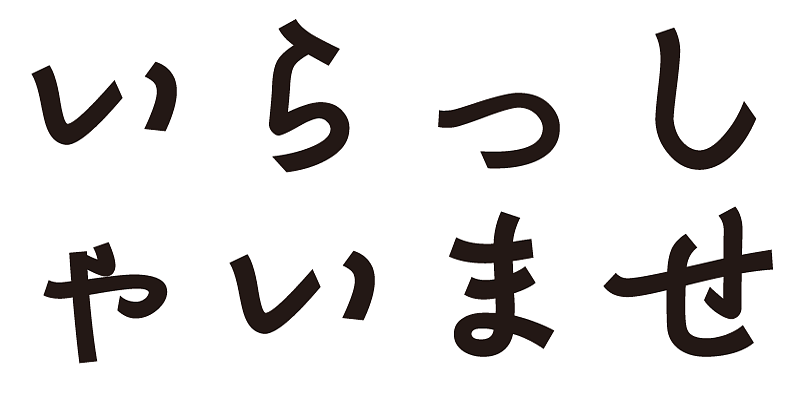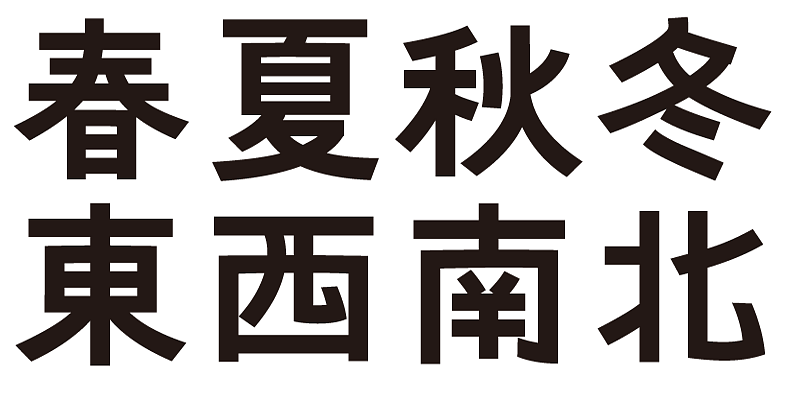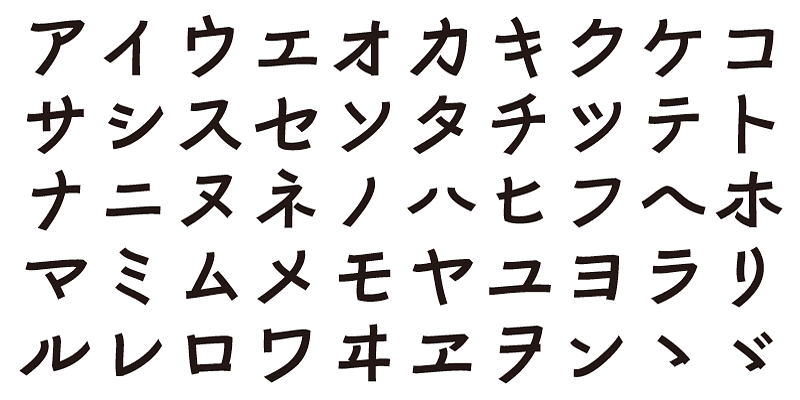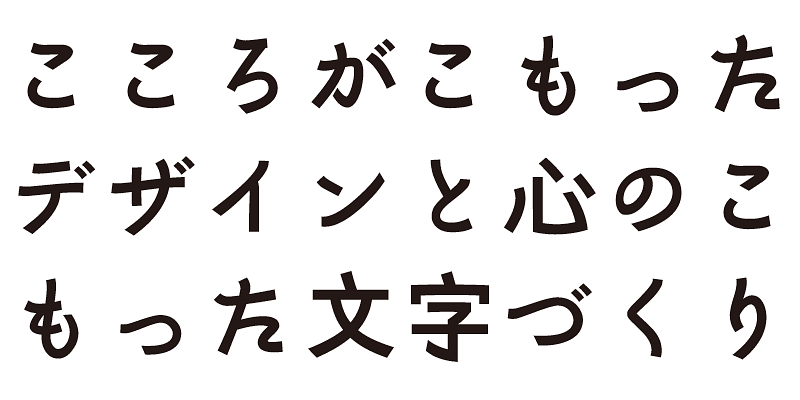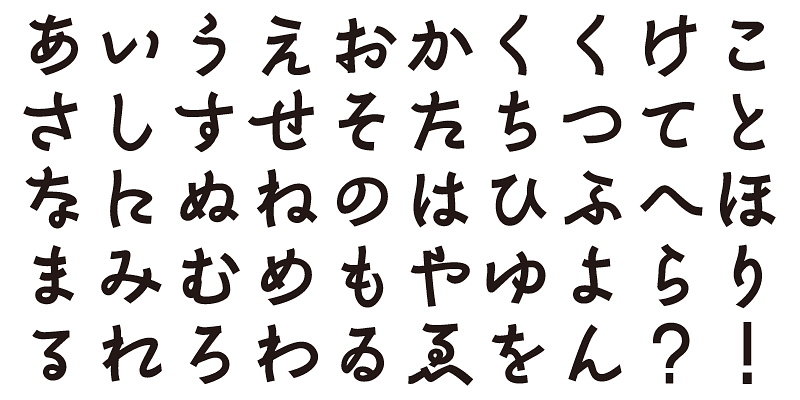
Diese Schrift im Gotikstil mit kräftigen Pinselstrichen basiert auf dem kalligrafischen Stil der chinesischen Sechs-Dynastien-Zeit (220–589 n. Chr.) sowie auf der traditionellen „Li Shu“-Kalligrafie (隶书; auch Clerical Script genannt).
Jede Schrift dieser Familie enthält neben 1.000 Kanji-Zeichen auch Hiragana- und Katakana-, alphanumerische und Interpunktionszeichen.
Wir entwerfen Schriften in der Hoffnung, dass sie den ausgedrückten Worten eine tiefere Bedeutung verleihen. Wir möchten, dass sich der Benutzer bei der Verwendung dieser Schriften wohlfühlt und Freude empfindet.